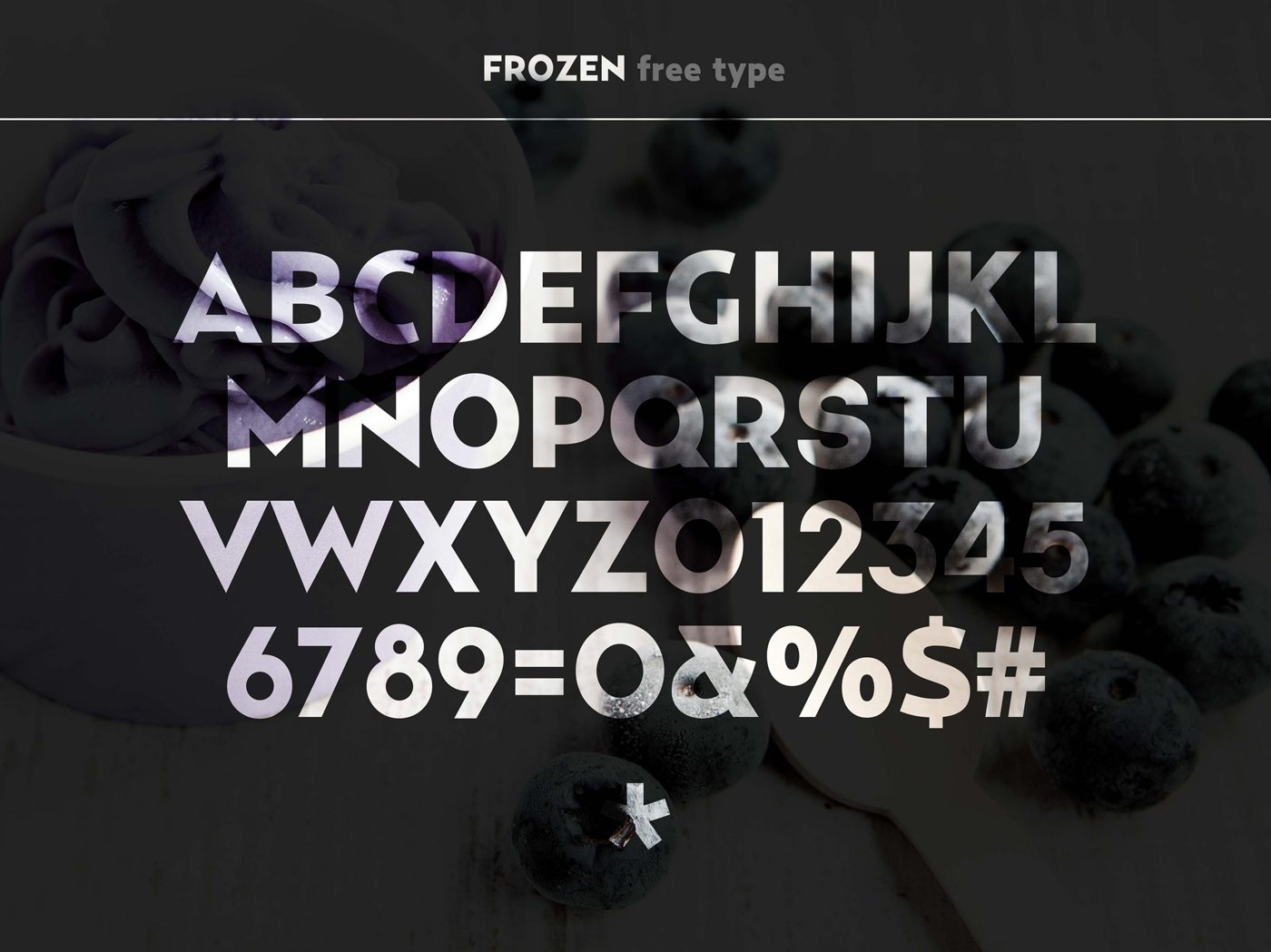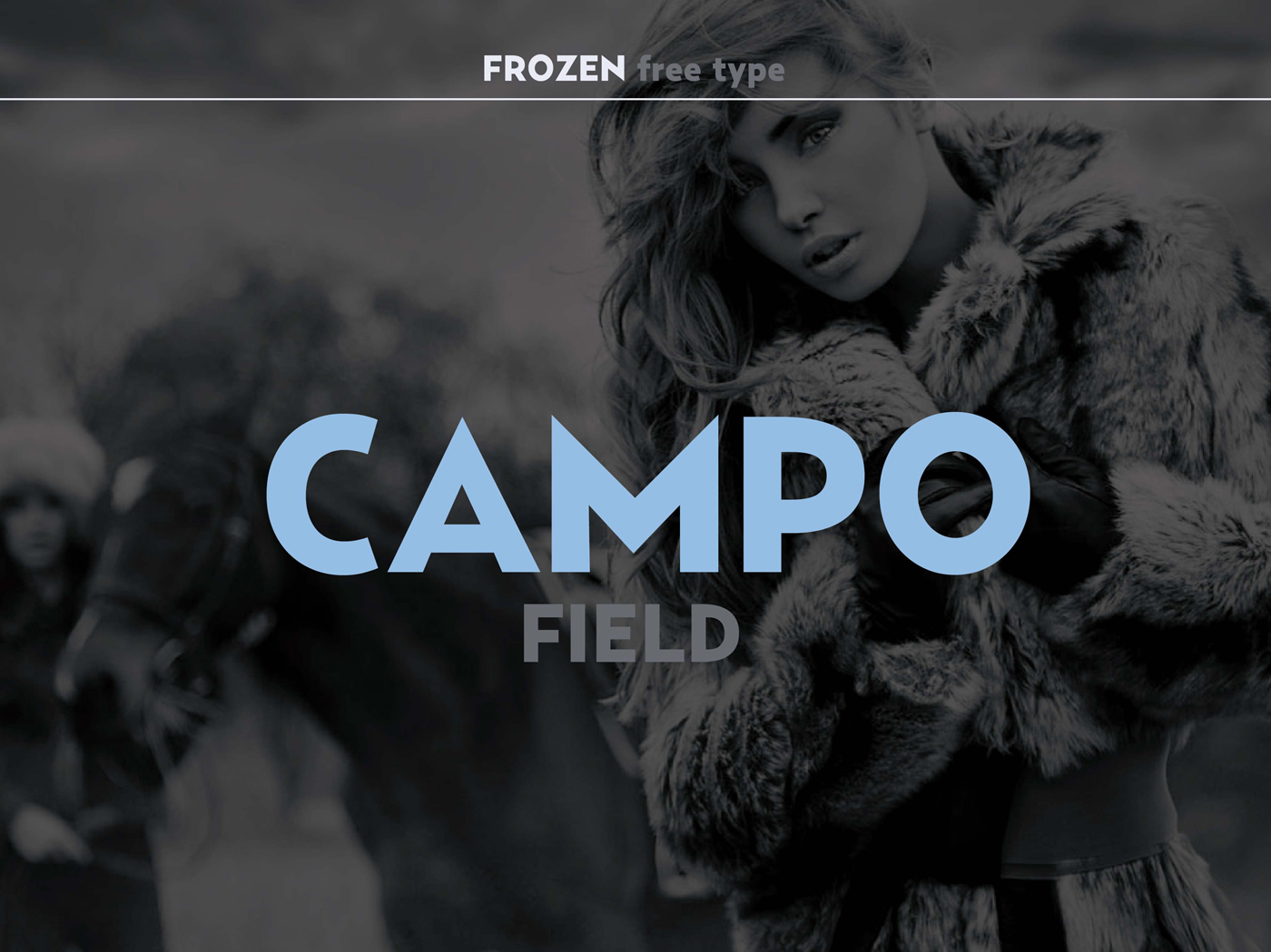
Otra semana más y ya llevamos 25 fuentes de texto gratuitas para descargar en nuestro especial a las fuentes tipográficas! El turno es para Frozen, una chula fuente sans serif en mayúsculas que os salvará más de una vez en alguno de esos proyectos que lleváis entre manos.